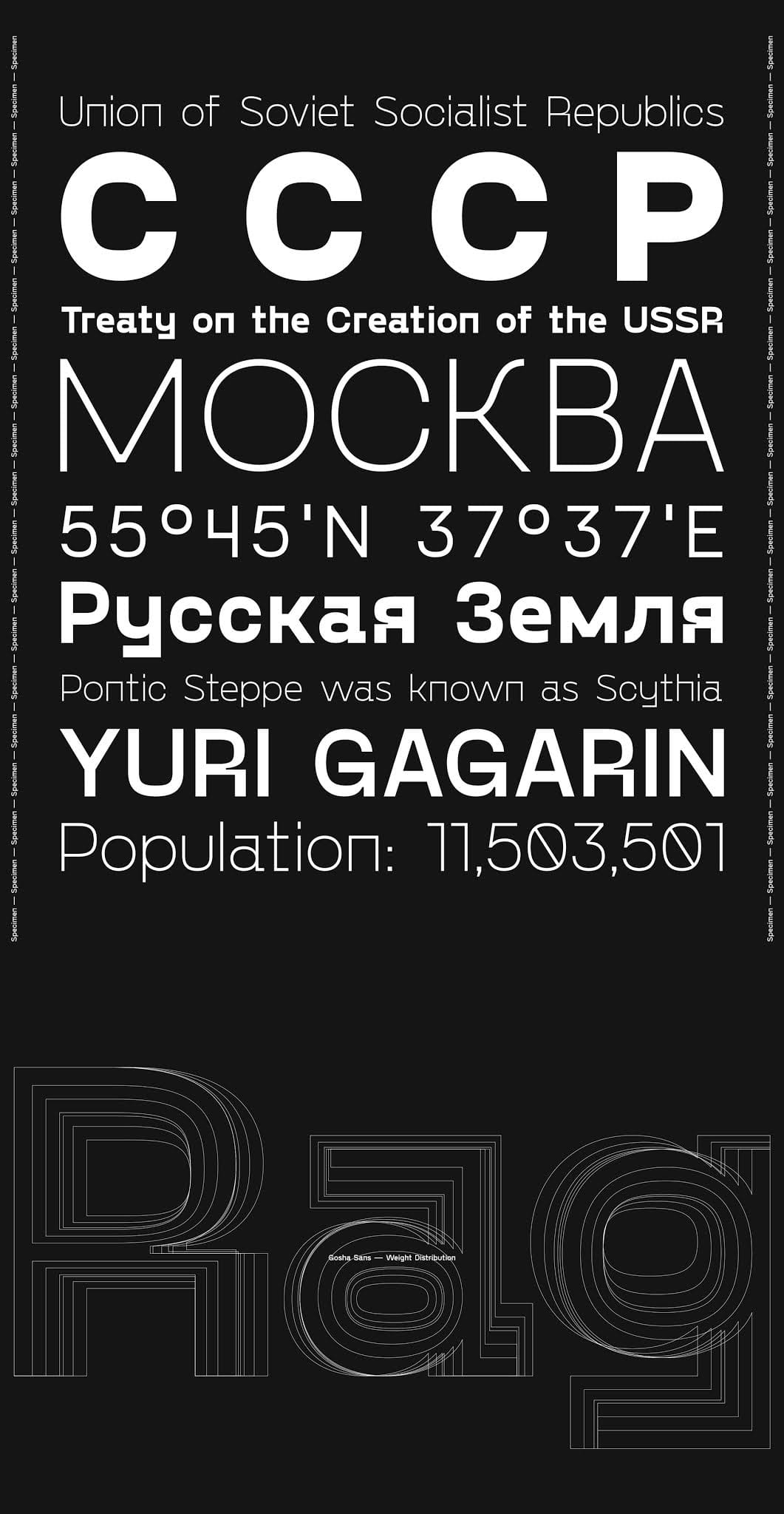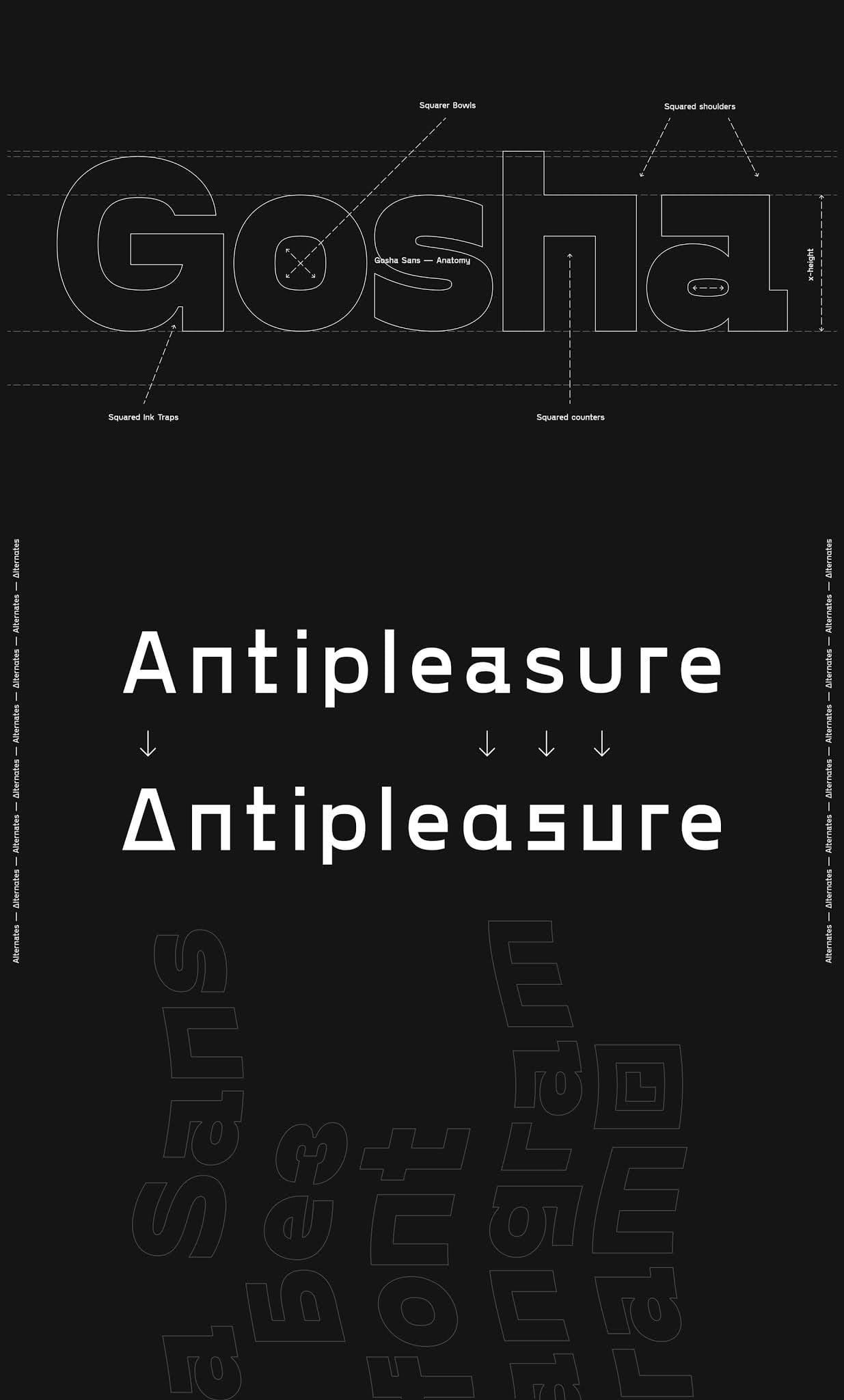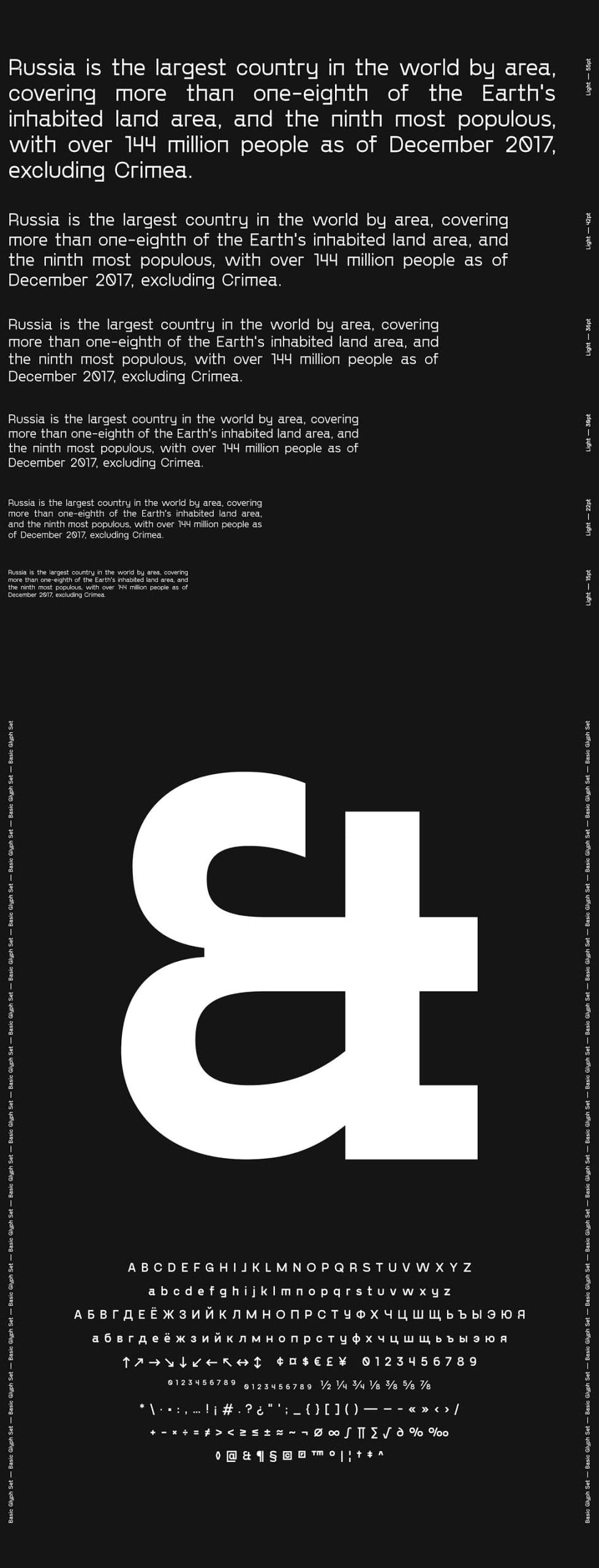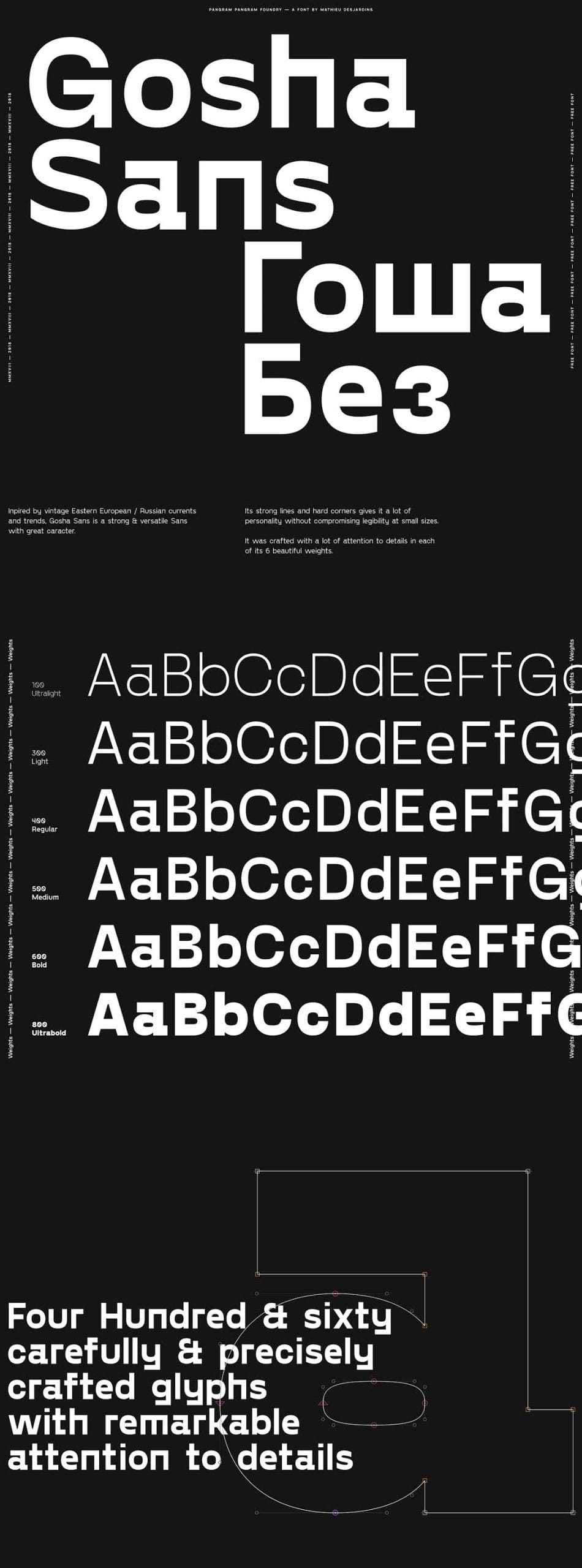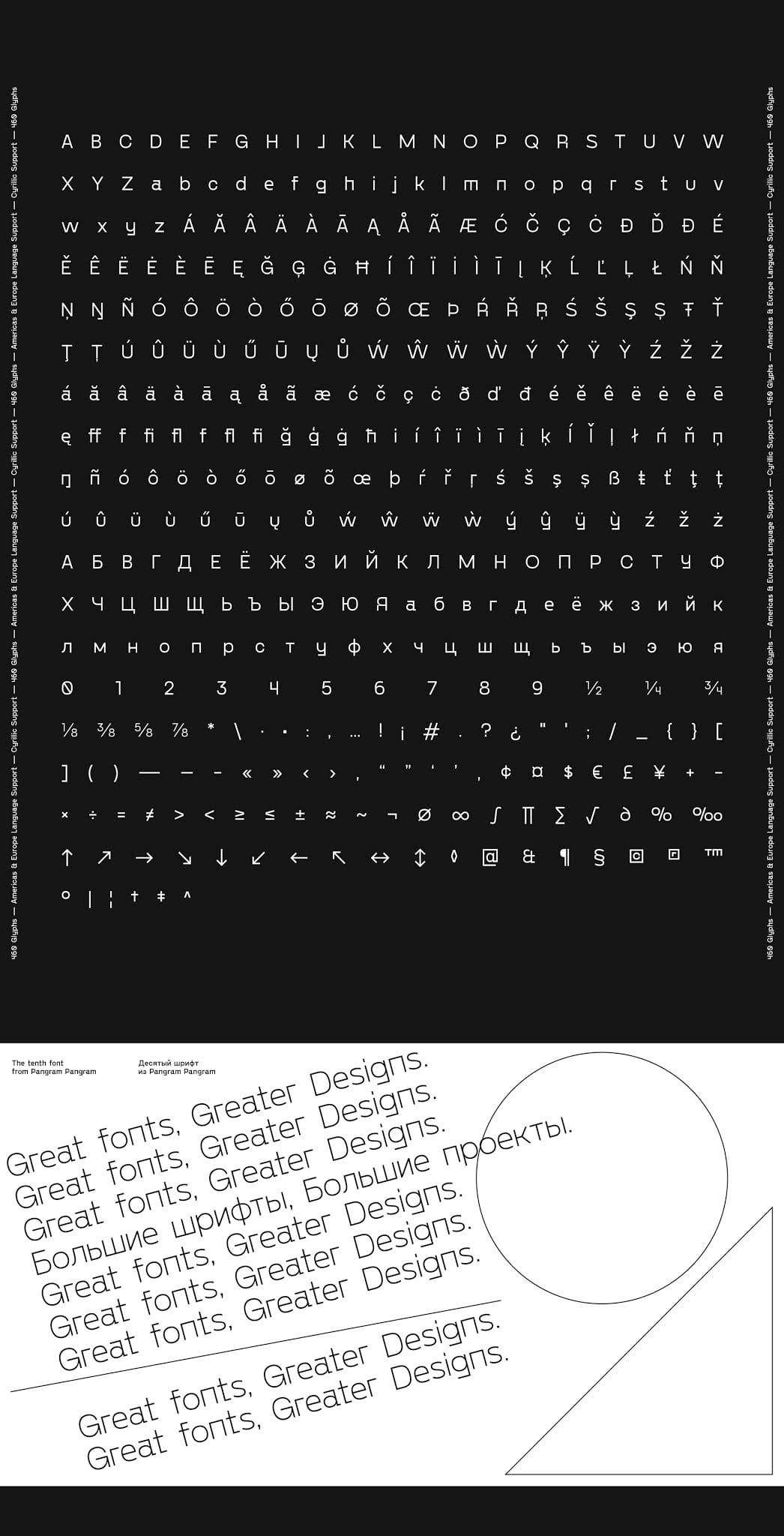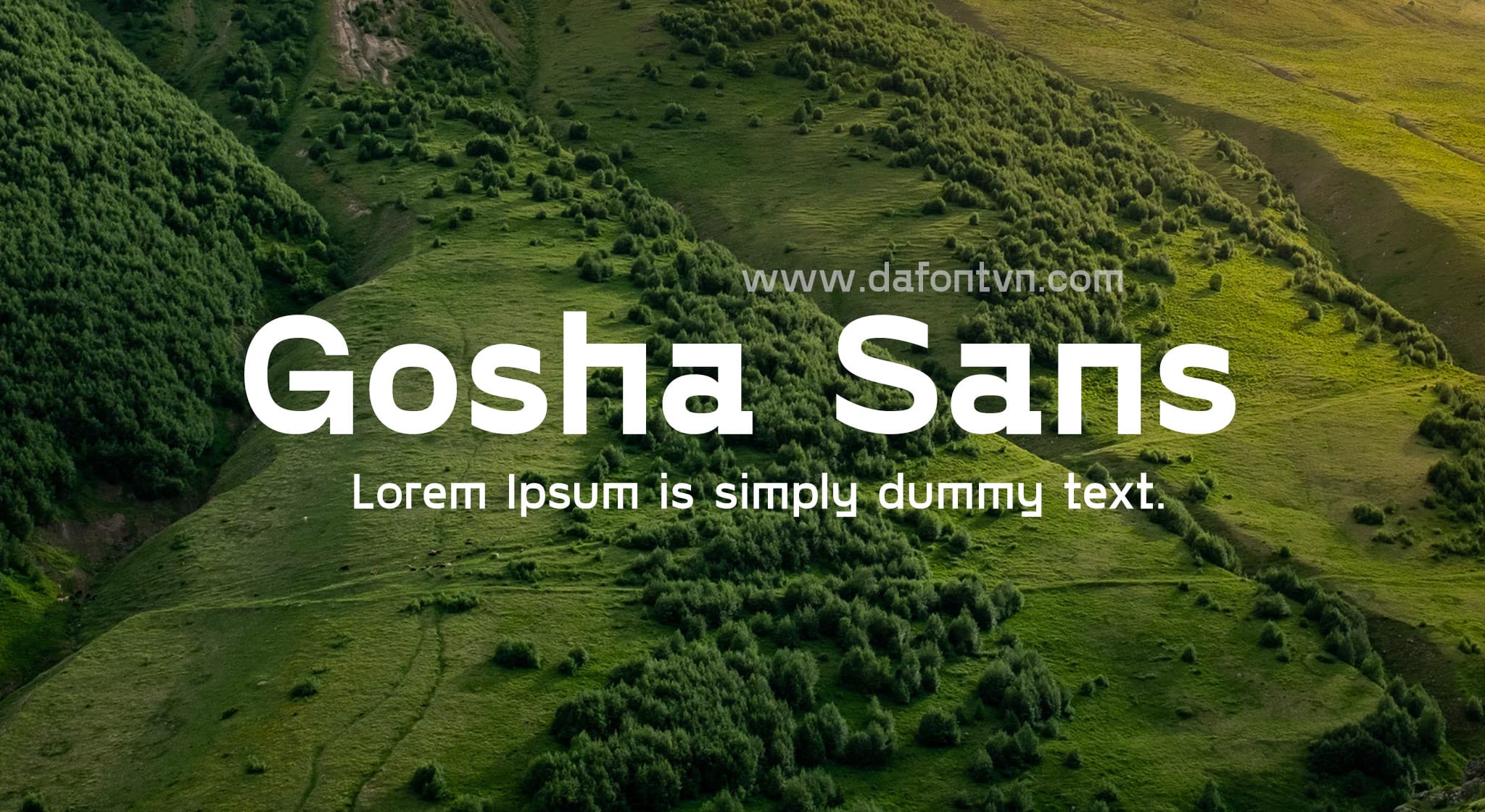
Gosha Sans là một Sans mạnh mẽ và linh hoạt với thiết kế tuyệt vời. Các đường nét mạnh mẽ và các góc cứng của nó mang lại cho nó nhiều cá tính mà không ảnh hưởng đến độ dễ đọc ở kích thước nhỏ.
Gosha Sans Font Family bao gồm 6 style với 620 glyph mỗi kiểu. Hỗ trợ ngôn ngữ cho Châu Mỹ, Nga và hầu hết Châu Âu. Thiết kế bởi Mat Desjardins.